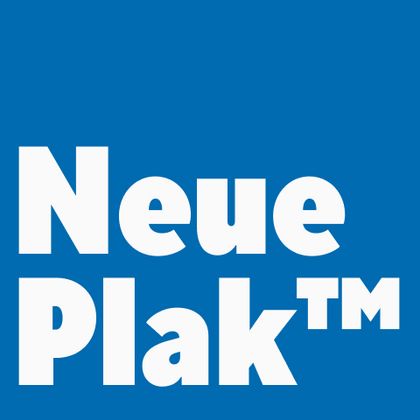
Шрифты похожие на Neue Plak™
Подборка этих шрифтов особенно хороша для рекламы, упаковки и брендинга — там, где нужны броские заголовки с характером. Если вам нравится шрифт Neue Plak™, наши плакатные гротески, где мощь форм сочетается с четкой геометрией, прекрасно подойдут для ваших проектов. В гарнитурах от TypeType сохранены фирменные черты — монолитные засечки, открытые контуры, поэтому они одинаково эффектно смотрятся как в гигантских билбордах, так и в интерфейсах мобильных приложений.
Если вы устали от «заезженных» шрифтов и ищете гарнитуры, похожие на Neue Plak™, ознакомьтесь с нашими лучшими альтернативами Neue Plak™. Это шрифты, которые имеют близкие характеристики, но в то же время обладают новыми уникальными особенностями дизайна. Например, относятся к той же категории шрифтов, подходят для тех же целей и имеют похожие черты, но отличаются в деталях или пропорциях.
Найдите отличную замену Neue Plak™ и попытайтесь имитировать похожее настроение, передать нужное вам ощущение, используя его в своих проектах. Каждый шрифт, представленный на этой странице, является двойником шрифта Neue Plak™, фактически его полным аналогом.